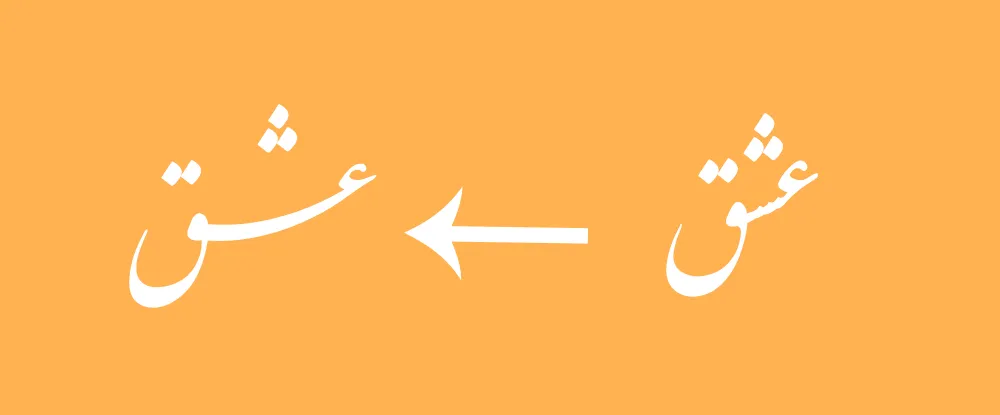
فونت نستعلیق نسخه 2
فونت نستعلیق Iran Nastaliq که به صورت استاندارد یونیکد طراحی شده است درجهت تولید و ساماندهی محتوای الکترونیکی ایران (تسما) و توسط شرکت داده ورزان هامون طراحی و پیاده سازی شده است, طرح تولید فونت فارسی نستعلیق از زمانی کلید خورد که دبیرخانه شورای عالی اطلاع رسانی کشور برای حضور در عرصه های بین المللی و نگارش رایانه ای کمر همت به پاسداشت فرهنگ پربار و غنی ایرانی بستند و ایم هم را به انجام رساندند.
کاربرد فونت نستعلیق فارسی :
- نوشتن متون: میتوان از فونتهای نستعلیق برای نوشتن انواع متون مانند شعر، نامه، مقاله و کتاب استفاده کرد.
- طراحی گرافیک: فونت نستعلیق برای فتوشاپ به دلیل زیبایی و ظرافتشان در طراحی گرافیک، تبلیغات، پوستر و صفحه آرایی نیز کاربرد دارند.
- حفظ و نشر فرهنگ: استفاده از فونتهای نستعلیق در فضای دیجیتال، به حفظ و نشر فرهنگ و هنر خوشنویسی ایرانی کمک میکند.
نمونه ای از کشیدگی حروف: